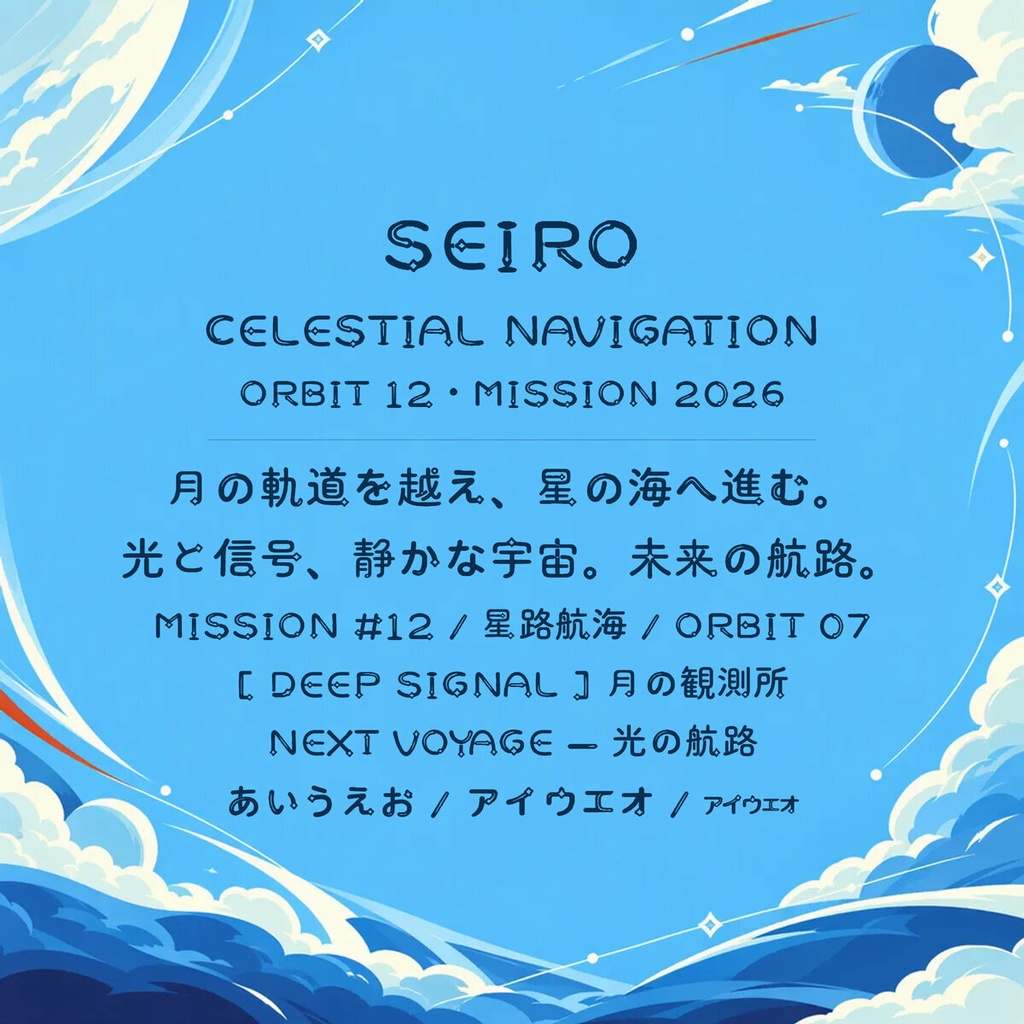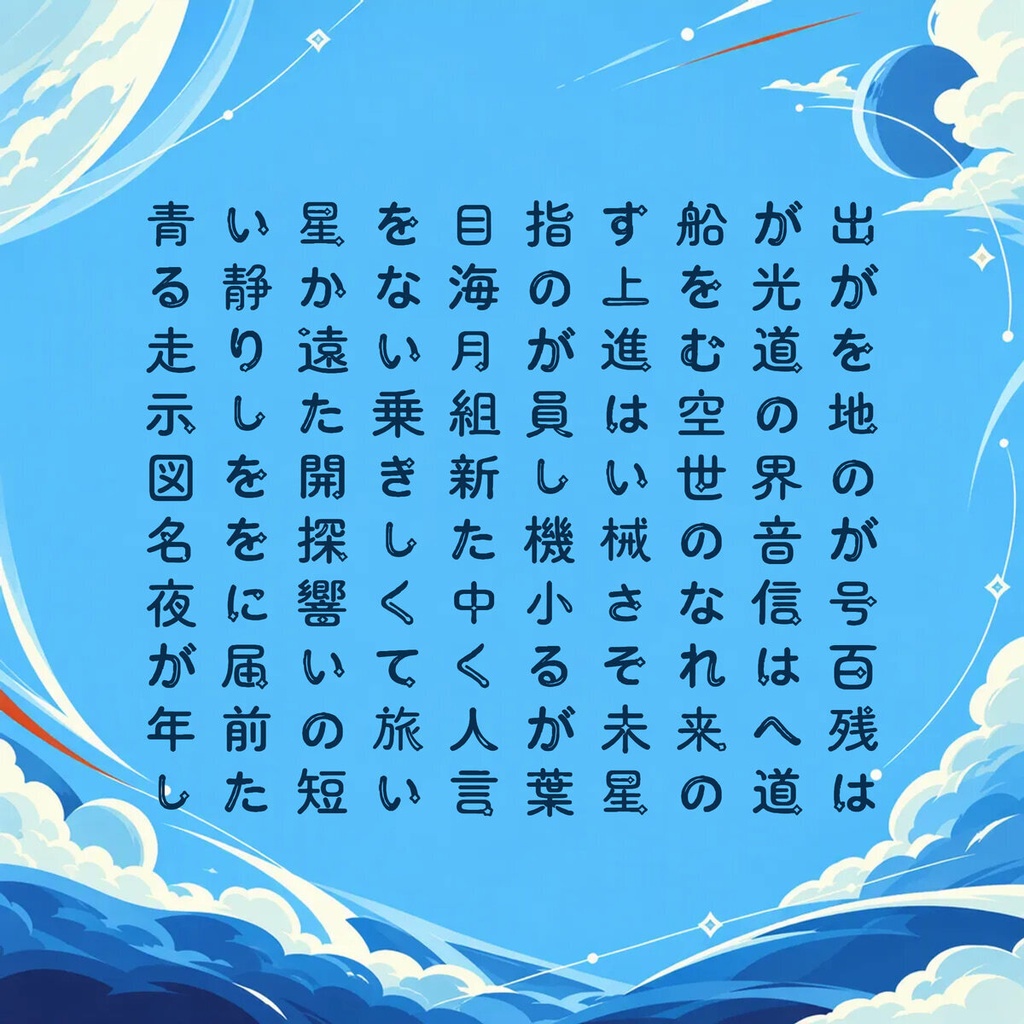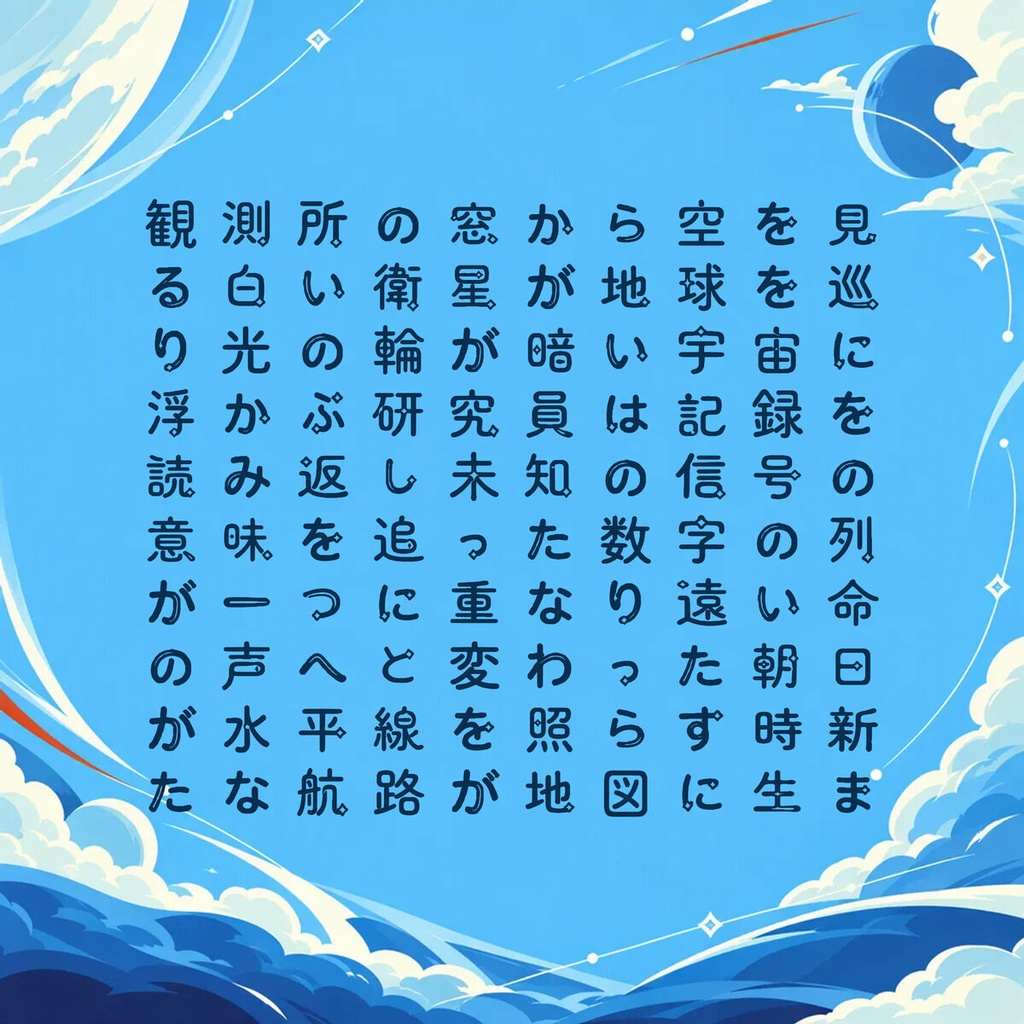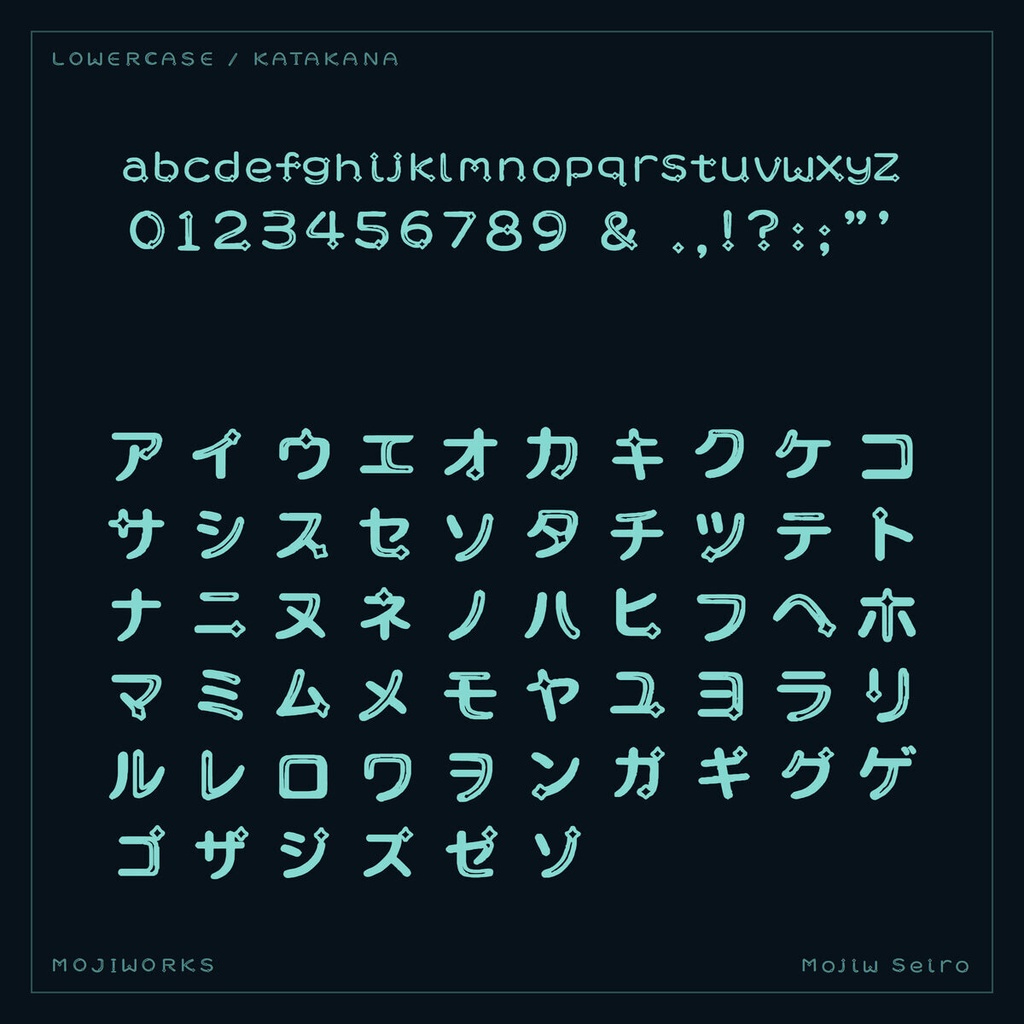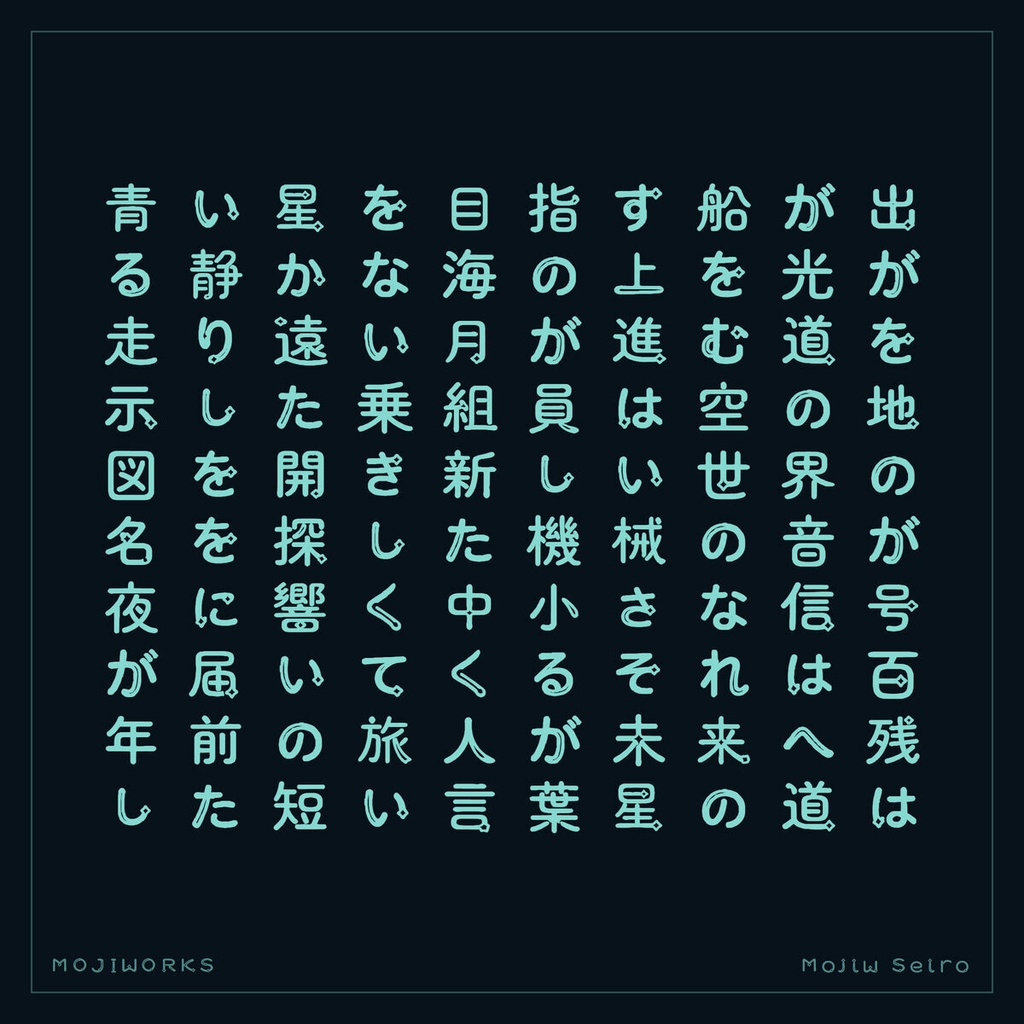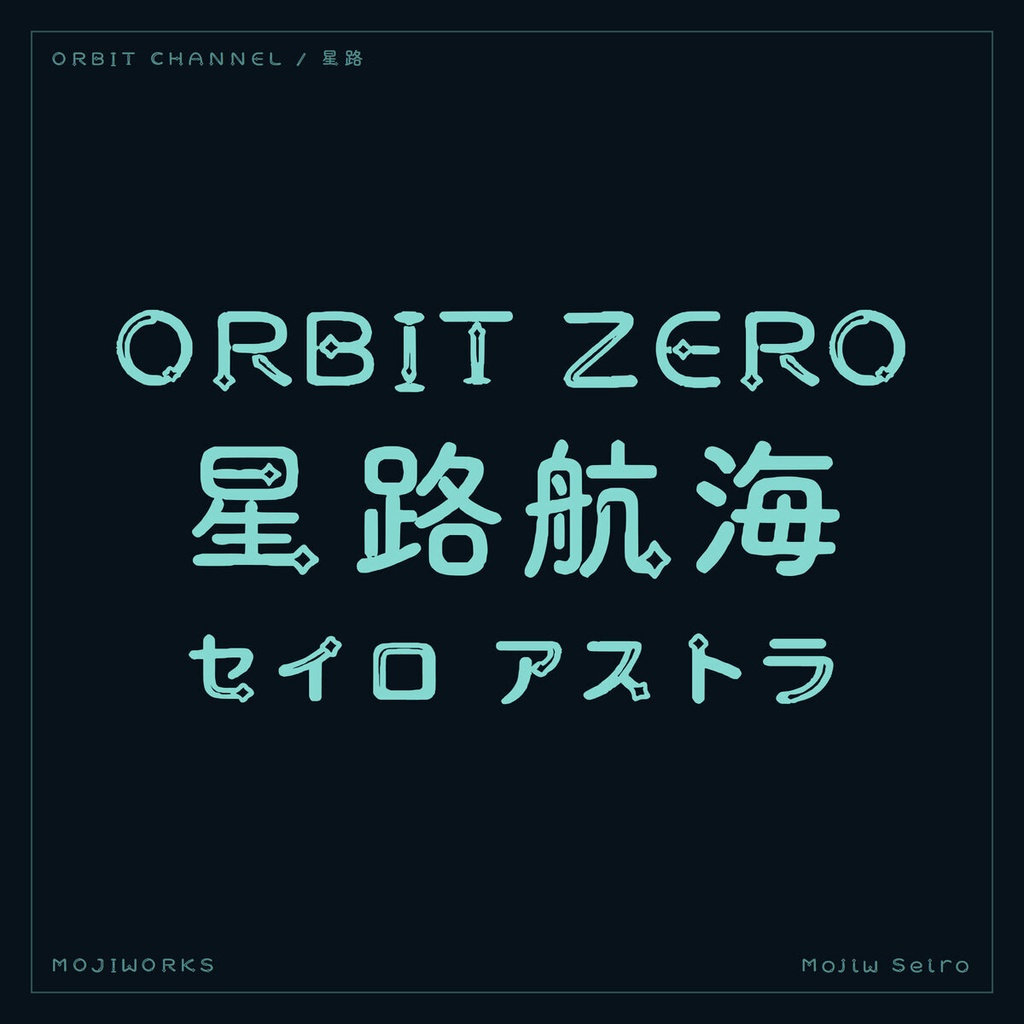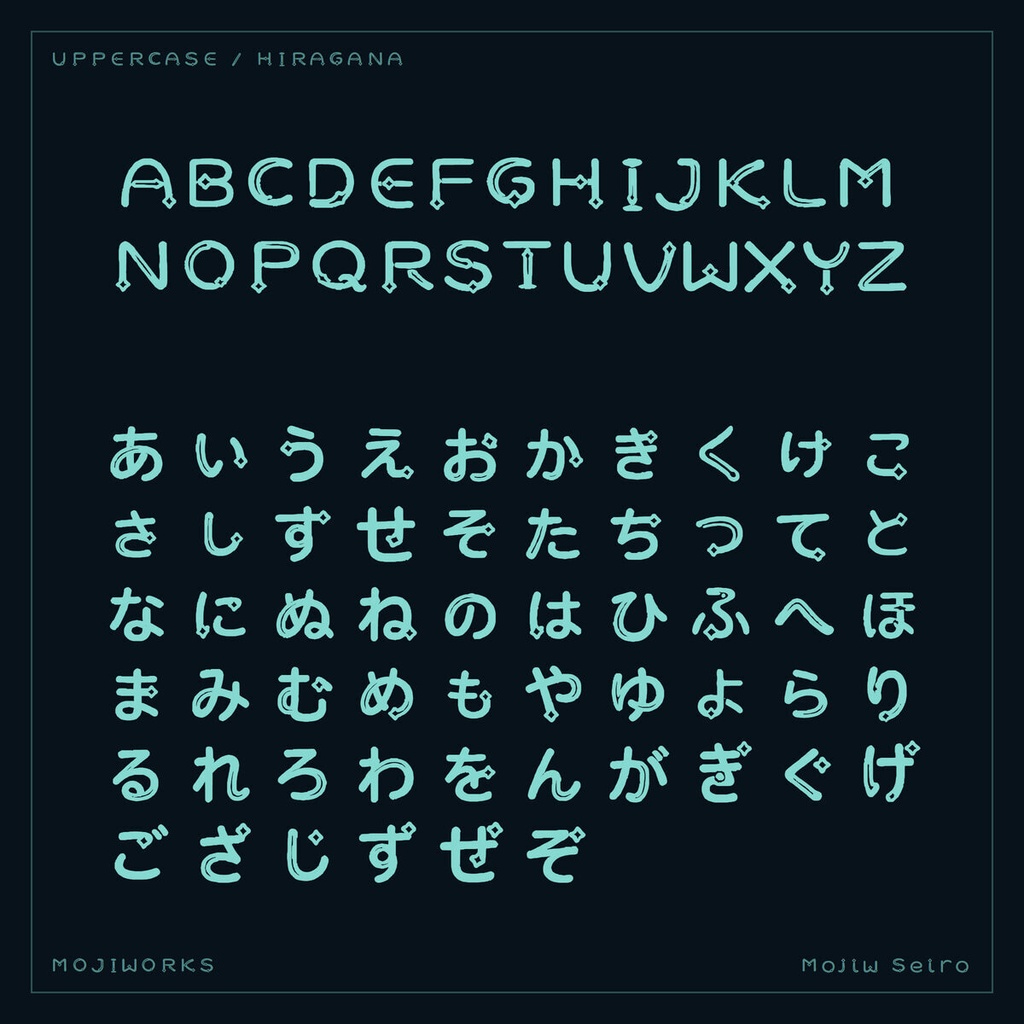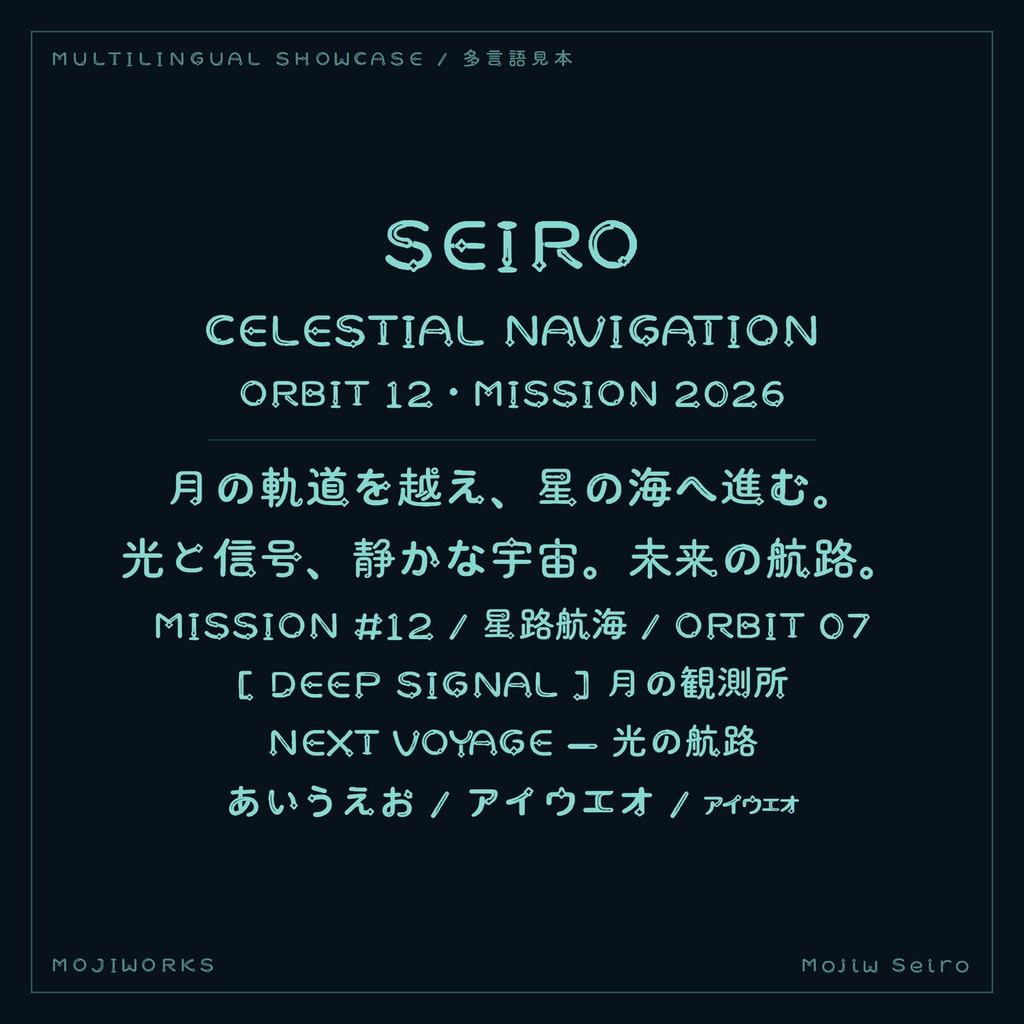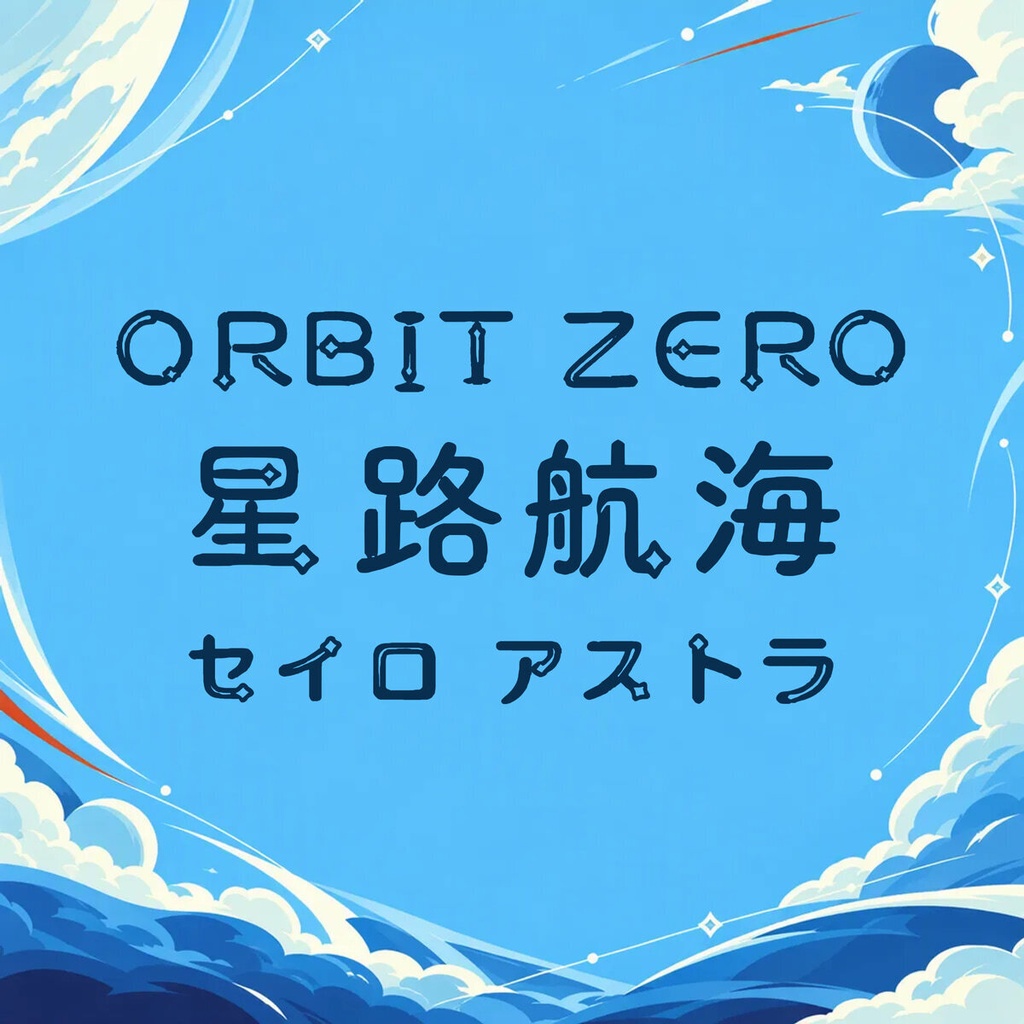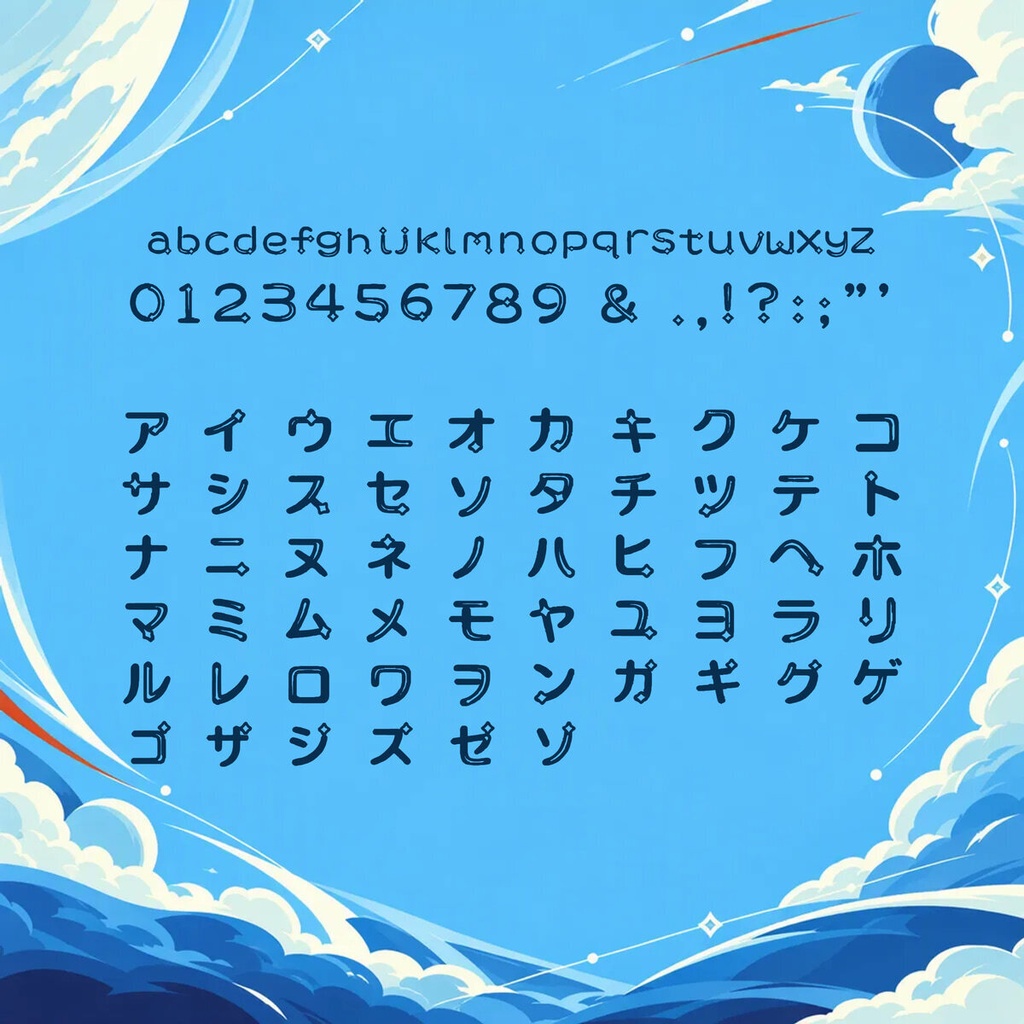
星路 Seiro【フォント】 — 軌道を描く宇宙書体|常用漢字2,136字
静かな月の周囲を巡る軌道を、文字の内部に刻んだ宇宙書体です。 A celestial display face mapped with orbital channels around a quiet artificial moon. 【用途 / Use】 SF / 宇宙 / ゲームUI / 配信画面 / テクノロジー For science fiction, space themes, game UI, streams, and technology. 【常用漢字フル版 / Joyo Complete】 常用漢字2,136字を完全収録し、ラテン文字・ひらがな・カタカナ・記号を含む全2,437文字を収録しています。半角カナは収録していません。 Includes all 2,136 Joyo kanji and 2,437 characters total, including Latin, hiragana, katakana, and punctuation. Half-width kana are not included. 2437文字 / characters 【関連する収録版 / Other Edition】 ラテン文字・かな・記号を収録したスタンダード版もあります。 The Standard edition includes Latin, kana, and punctuation. ▶ スタンダード版 / Standard: https://mojiworks.booth.pm/items/8826757 【フォント仕様 / Specification】 バージョン / Version: 1.0.1 形式 / Format: TrueType (.ttf), Web (.woff2) 対応環境 / Platform: Windows, macOS, web browsers 収録字一覧 / Character list: CHARSET.txt 同梱 / Included: font files, README, LICENSE, character list, portfolio PDF, product previews. 【利用規約 / License Summary】 個人・商用利用可。1ライセンスは購入者1名に適用されます。 Personal and commercial use is permitted. One license covers one purchaser. 印刷・動画・ロゴ・グッズ等の静的成果物、および購入者が運営するサイトでの同梱WOFF2の利用が可能です。 Static output such as print, video, logos, and merchandise is permitted. The bundled WOFF2 may be used on a website owned or operated by the purchaser. ゲーム・アプリへの組み込みは、利用者が生のフォントを抽出できない形式に限ります。生のフォントを同梱する場合は別途ライセンスをご相談ください。 Game/app embedding requires protection against extraction of the raw font. Contact us for a separate runtime-embedding license when shipping raw font files. 標準ライセンスは1製品・1サイトあたり年間約100,000ユーザーまで。従業員50名超の組織を含む大規模利用は要相談。 Standard coverage is approximately 100,000 users per product/site/year. Larger use and organizations with more than 50 employees require an extended license. フォント本体の再配布・販売・貸与・変換・グリフ抽出・派生フォント制作・生成AI学習やスタイル参照は禁止です。 Redistribution, resale, lending, conversion, glyph extraction, derivative fonts, and generative-AI training or style reference are prohibited. 完全な利用条件は同梱の LICENSE.txt / LICENSE.jp.txt をご確認ください。 The bundled license files are authoritative; consult them for the complete terms. 【ほかのフォント・カスタム制作 / More Fonts and Custom Work】 フォント一覧、オーダーメイド書体、文字追加、拡張ライセンスのご相談はこちら。 Browse our catalog or contact us for custom typefaces, added characters, and extended licenses. https://mojiworks.booth.pm/